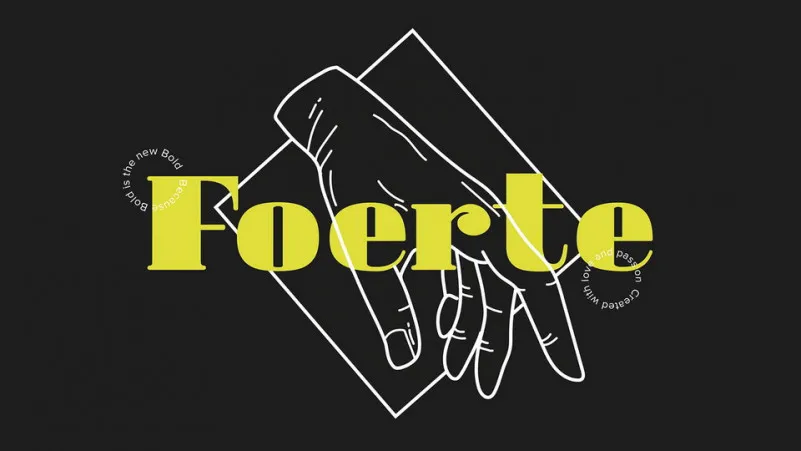
Aqui está uma descrição envolvente e natural para a página de download da font ‘Foerte Serif Font’ no formato solicitado: Nossa nova seleção é Foerte Serif, um belo tipo serif com aparência moderna e sofisticada. Inspirada em antigos postais luxuosos, essa elegante fonte combina elementos dos tempos passados com a simplicidade de hoje, criando uma experiência visual única que se adapta perfeitamente para qualquer projeto design. Foerte Serif é um tipo bold e forte, ideal tanto para aplicações comerciais quanto para expressar seu estilo ou produto de forma profissional. Perfeito para gráficos de apresentação e infográficos – Foerte proporcionará uma aparência sofisticada e atraente que certamente se destacará em qualquer projeto. Se você é um designer em busca de uma fonte elegante para estilos de exibição, Foerte foi feito para você. Esta fonte elegante combina o bom gosto da era moderna com os elementos únicos dos tempos passados, criando um mix perfeito que certamente será um recurso valioso em seu portfolio. Não importa se é um cartaz de propaganda ou uma apresentação de design de produto – Foerte está aqui para ajudar a ilustrar sua mensagem de forma profissional e inovadora. Experimente Foerte Serif no próximo projeto e desfrute da experiência visual única que oferece, um verdadeiro blend entre o passado e o presente. Foerte é uma fonte que você vai querer usar sempre!